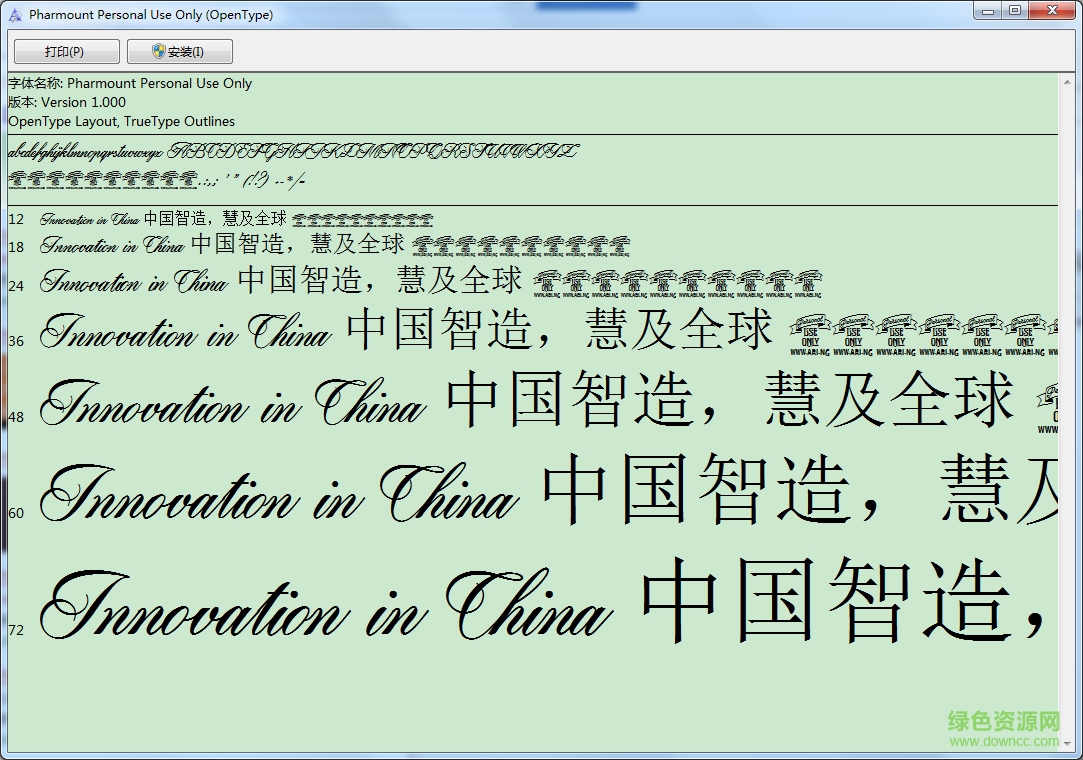
Pharmount字體
Pharmount是一款斜體的復(fù)古英文字體,此款字體線性飄逸,整體效果優(yōu)雅美觀,廣泛的應(yīng)用于平面設(shè)計(jì)、廣告設(shè)計(jì)、排版印刷、名片設(shè)計(jì)等各行各業(yè),喜歡的朋友歡迎來綠色資源網(wǎng)下載!